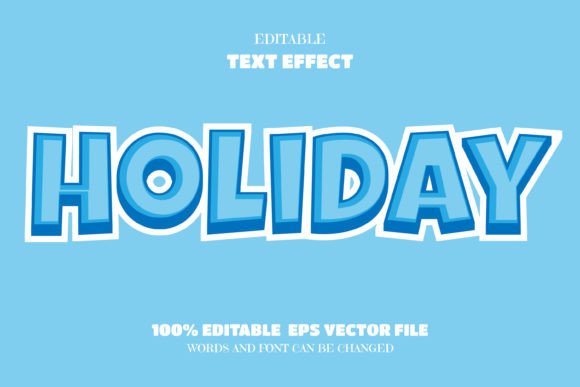
Holiday Text, Editable Font Effect
Die richtigen Designelemente zu finden, kann eine Herausforderung sein, aber Holiday Text, Editable Font Effect bietet eine außergewöhnliche Sammlung, die Ihre Arbeit sofort aufwertet.
Mit Präzision gefertigt, bietet Holiday Text, Editable Font Effect saubere Vektoren, eine reibungslose Typografie und eine kommerzielle Lizenz für ein beruhigendes Gefühl.
Egal, ob Sie POD-Produkte (Print on Demand), Hochzeitseinladungen oder Social-Media-Grafiken erstellen, Holiday Text, Editable Font Effect ist die ideale Wahl.
Experten-Tipp: Kombinieren Sie diese Elemente mit ergänzenden Schriftarten, um einzigartige, auffällige Designs zu kreieren.